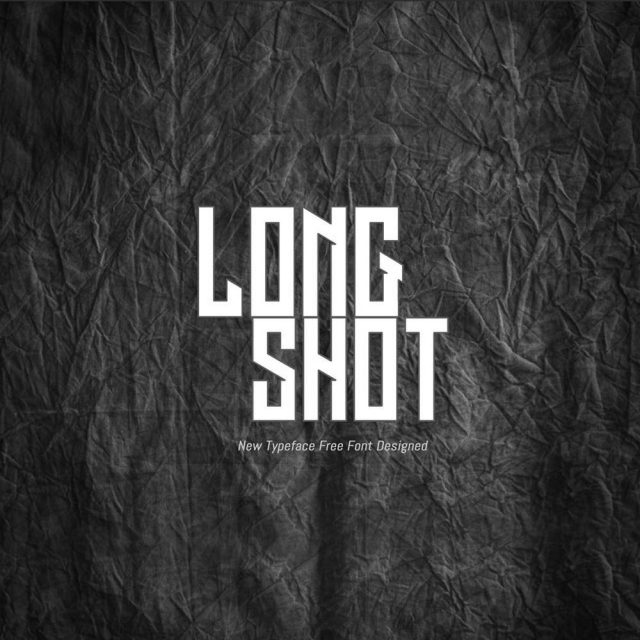
فونت پرمیوم و انگلیسی Long Shot Font یک فونت منحصر به فرد است که با کاراکترهایی با طول و ارتفاع استثنایی متمایز میشود و سبک بصری چشمگیر و نامتعارفی را ایجاد میکند. Long Short با خطوط دقیق و تمیز خود، ضمن حفظ تعادل هماهنگ، حال و هوایی مدرن و پیچیده را به نمایش میگذارد. این فونت برای پروژههای طراحی که نیاز به خلاقیت و فاصله گرفتن از هنجارها دارند، ایدهآل است – از پوسترهای تبلیغاتی و بستهبندی محصولات گرفته تا رسانههای چاپی مانند مجلات و کتابها. این فونت با حرکات باریک و همهکاره خود، برای طیف گستردهای از کاربردها – از جلد کتاب و پوستر گرفته تا تلاشهای خلاقانه مانند طراحی لوگو، بنر و فراتر از آن – مناسب است.
مزایای استفاده از فونت لاتین Long Shot چیست؟